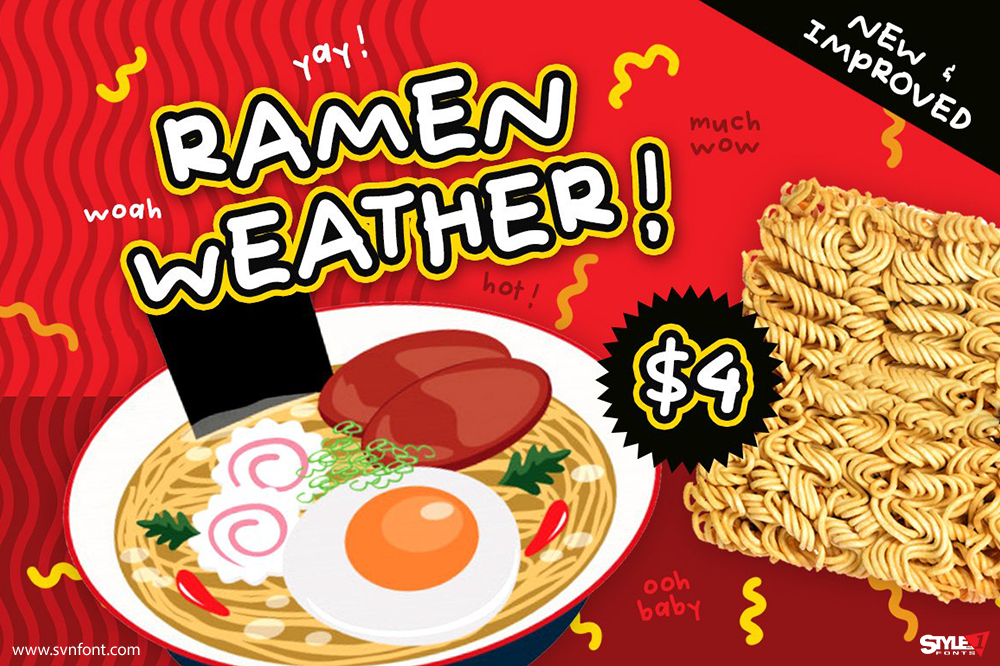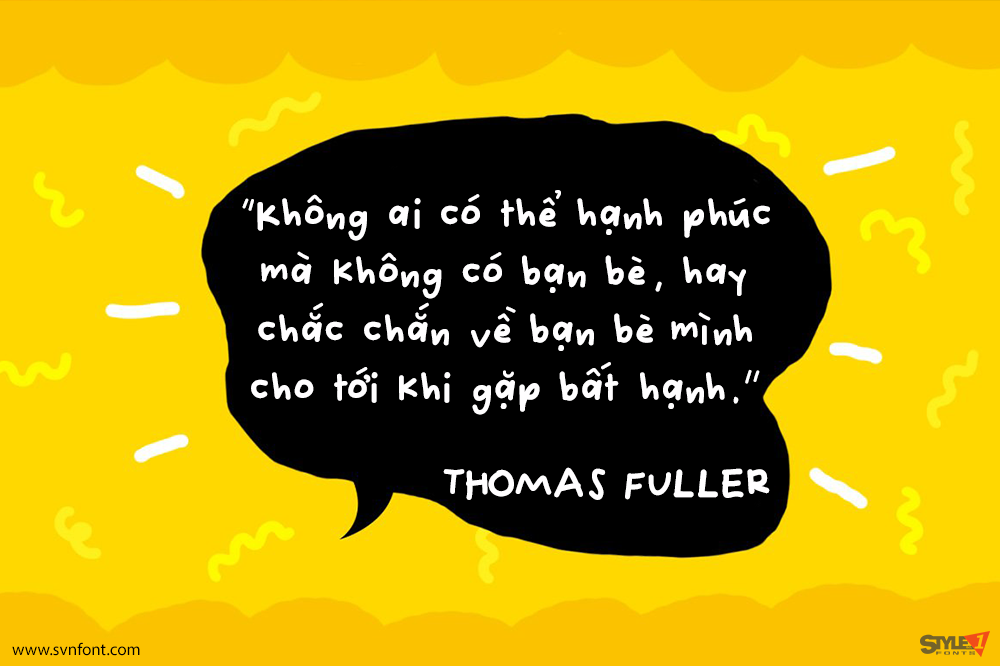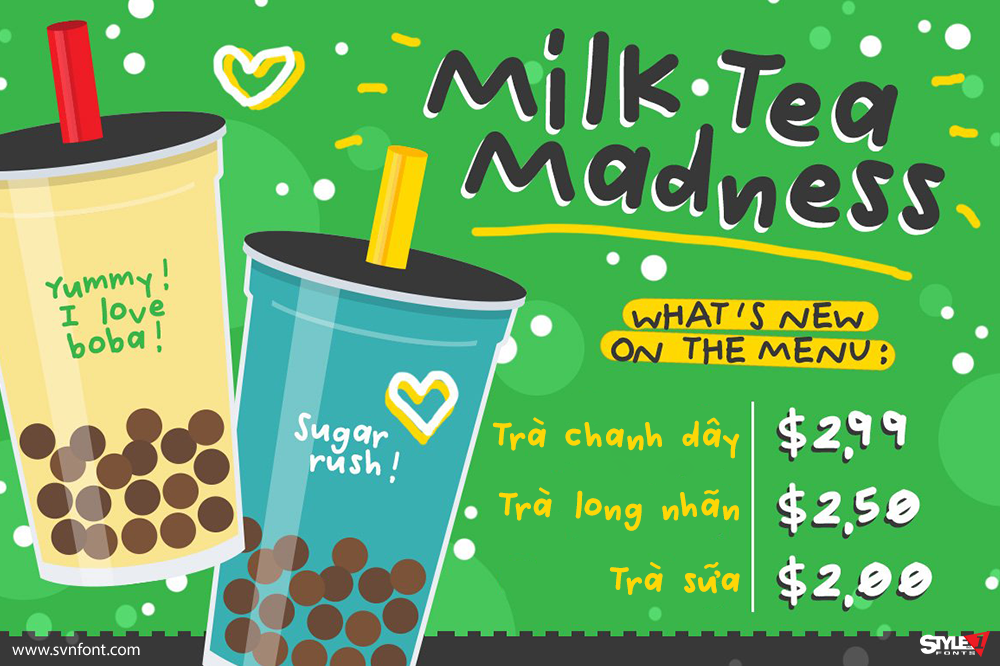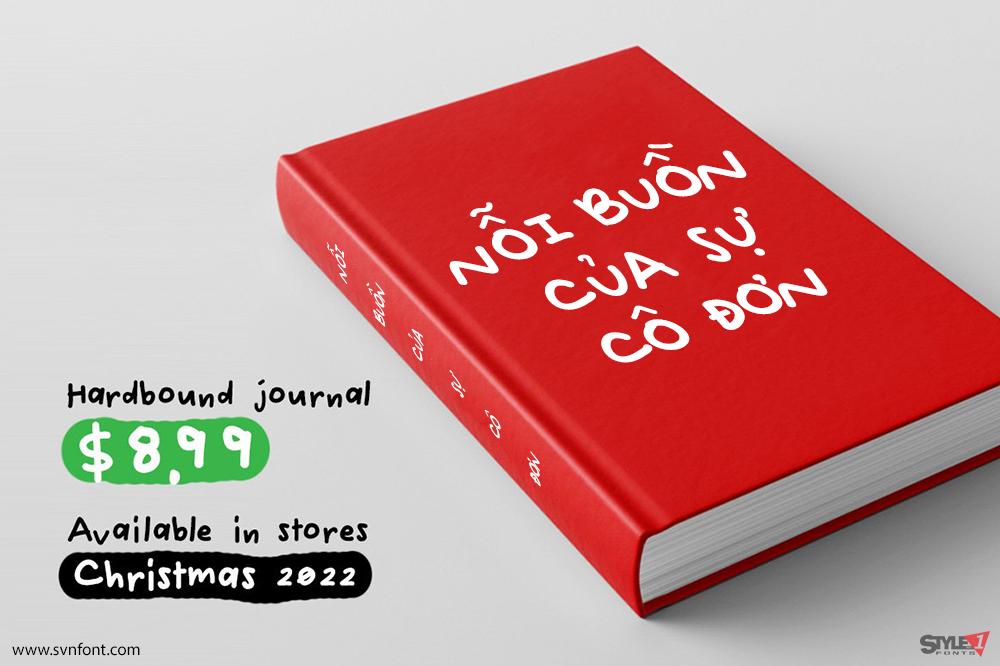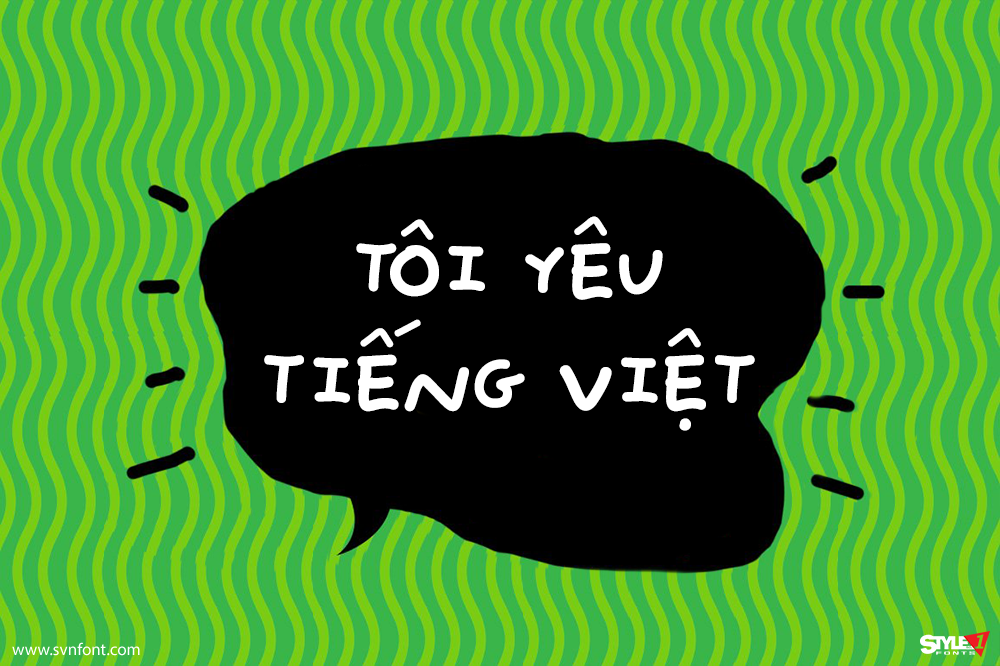
Siêu duyên dáng và siêu dễ thương, Chicken Noodle Soup là một font chữ viết tay hoàn hảo mang cảm giác thoải mái, vui vẻ và vô tư. ✨
Font này rất phù hợp cho thiệp mời tiệc sinh nhật, thiết kế mạng xã hội, poster, và bất kỳ dự án nào cần đường baseline hơi lệch tự nhiên cùng vẻ viết tay rõ ràng, dễ đọc. Nhờ đó, Chicken Noodle Soup hoạt động hiệu quả cho cả tiêu đề lẫn nội dung văn bản, mang lại cảm giác gần gũi và tràn đầy năng lượng tích cực.